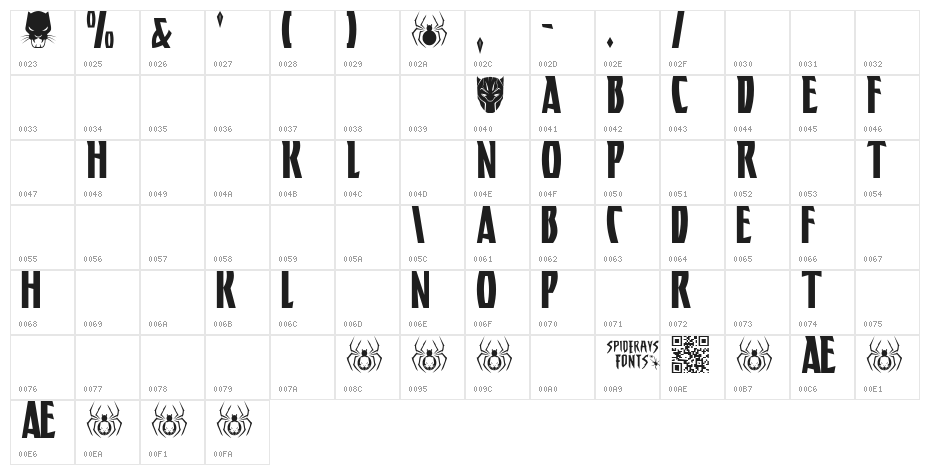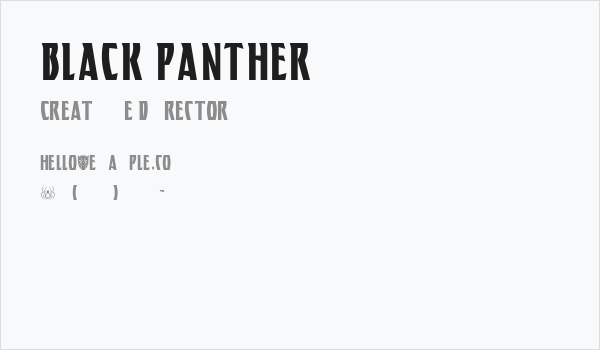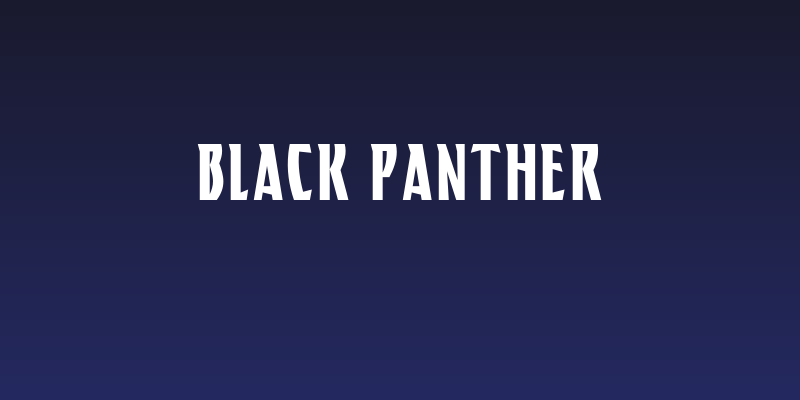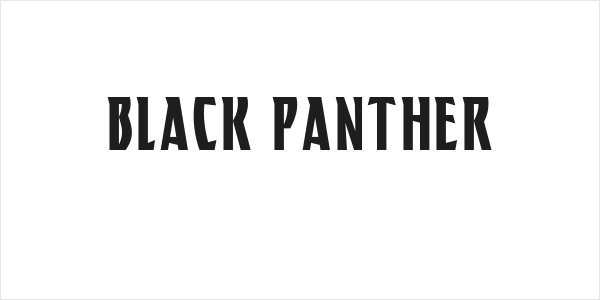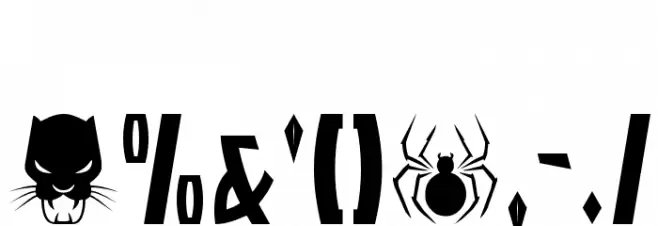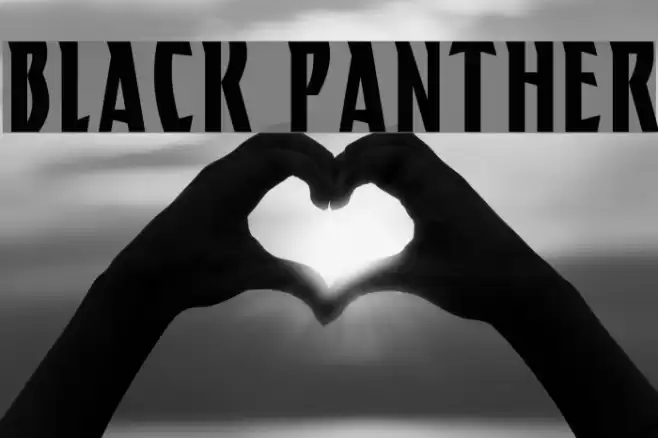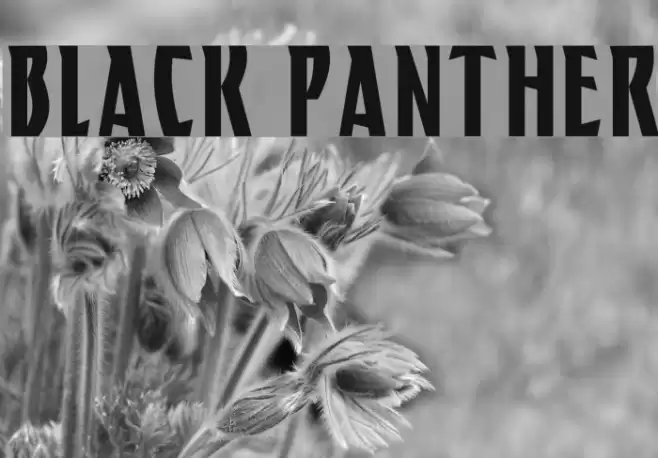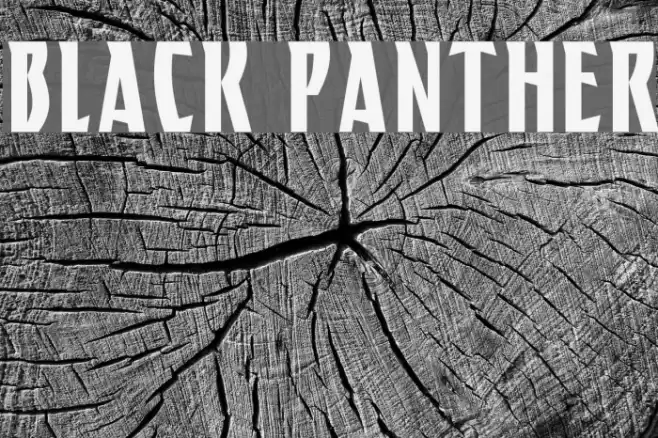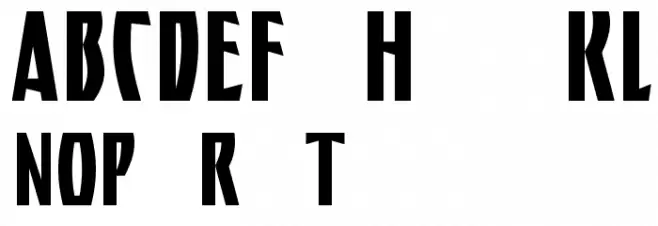
BLACK PANTHER Font
BLACK PANTHER
| Style général | Modern, Decorative |
| Projets proposés | Ideal for comic book covers, movie posters, branding for action-themed products, or any project needing a bold, impactful typeface. |